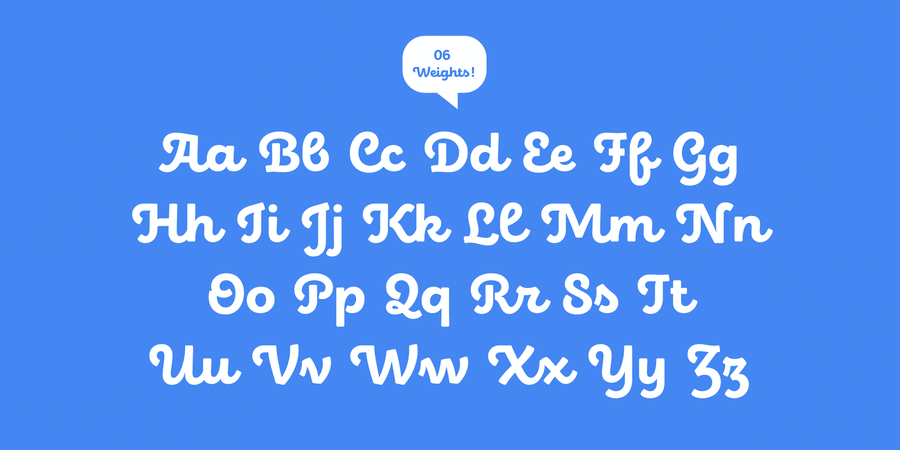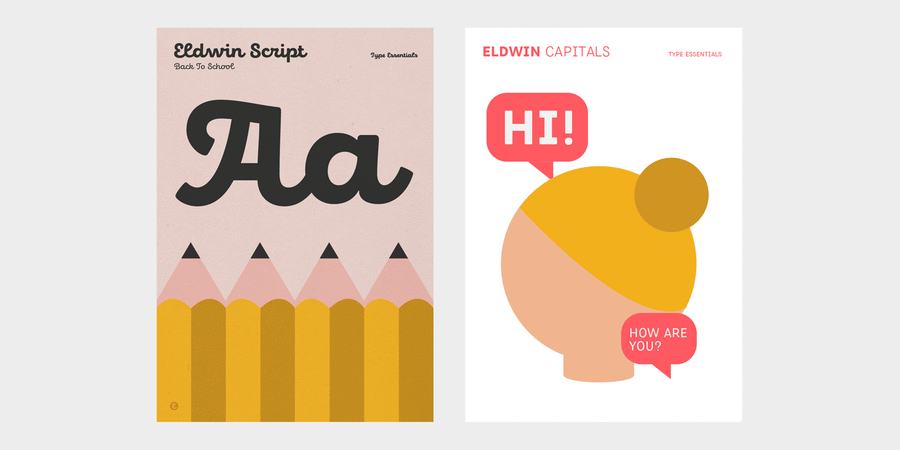
Eldwin – це енергійний з'єднаний рукописний шрифт з доброзичливим характером. Завдяки каліграфічним і гротесковим накресленням, що доповнюють одне одного, шрифт поєднує в собі грайливість і функціональність, що дозволяє йому найкращим чином працювати в таких ситуаціях, як меню і упаковка, журнали і реклама. Натхненням для Елдвіна став традиційний італійський та американський сайн пейнтінг. Розробка шрифту почалася з малюнків на папері, які потім перетворилися в цифровий шрифт. Сімейство включає 6 насиченостей у двох стилях (Script і Capitals) з латиницею і кирилицею, альтернативними гліфами та лигатурами. Шрифт розробила Ксенія Білоброва у 2017 році. Eldwin™ є торговою маркою компанії The Northern Block.
12 накреслень
Асоціації з сімейством шрифтів EldwinОсобистість і характер гарнітури:
тонкий, худий, легкий, хіпстерський, добрий, наївний, милий, М'який, динамічний, рукотворний, ручний, екологічний, доброзичливий, довірчий, зелений, натуральний, природний, теплий, ламповий, гнучкий, модний, грайливий, потішний, гладенький, прикольний, привітний, красивий, свіжий, характерний, акуратний, мотузковий, круглий, симпатичний, неоновий, делікатний, інтимний, дротяний, приємний, чистий, ніжний, рівний, якісний, чесний, здоровий, бадьорий, святковий, домашній, крафтовий, літній, няшний, смачний, ввічливий, культурний, гармонійний, оригінальний, пластичний, затишний, комфортний, зрозумілий, ясний, радісний, дитячий, щасливий, рослинний, мирний, апетитний, соковитий, стиглий, солодкий, сімейний, ремісничий, артізанальний, побутовий, ледачий, щедрий, фруктовий, ягідний, спекотливий, тропічний, яскравий, виразний, помітний, рясний, насичений, прозорий, статичний, прохолодний, сучасний, лаконічний, невагомий, крихкий, повітряний, спокійний, універсальний, Простий, врівноважений, ненав'язливий, помірний, непомітний, практичний, доступний, стійкий, твердий, добродушний, cтрогий, переконливий, серйозний, формальний, мотивуючий, відповідальний, добротний, консервативний, старомодний, міський, точний, пластмасовий
хенд мейд, відпочинок, природа, море, пляж, квіти, щоденник, зошит, прикраса, селфі, Хюґе, дієта, сніданок, АСМР, чистота, гігієна, Інстаграм, графіка, ілюстрація, ранок, світанок, велнес, кафе, їжа, розваги, свято, табір, школа, дитяча книжка, смузі, ресторан, краса, лосьйон, шампунь, готель, чай, фломастери, літо, молоко, іграшка, гра, мультфільм, канікули, учень, школяр, дім, йога, небо, торгівля, продукти, ремесло, ярмарок, фаст фуд, закуска, крамниця, одяг, взуття, десерт, подарунки, кондитерська, булочна, сік, торт, варення, шоу, телебачення, шаурма, соус, кетчуп, здоров'я, преміум, шоколад, родина, магазин, зоомагазин, тварини, фермер, чіпси, сир, піцца, жуйка, підгузок, фрукти, мармелад, лобстер, зоопарк, кава, кондитер, булочка, солодощі, лікер, коктейль, обід, бар, фарба, цукерки, мафін, морозиво, випічка, пластилін, день народження, дитячий ранок, дитсадок, дитяче харчування, парфумерія, туалетна вода, косметика, мода, інтер'єр, Місто, вода, прилад, суспільство, ліки, латте, аптека Гарнітура має ознаки стилів: